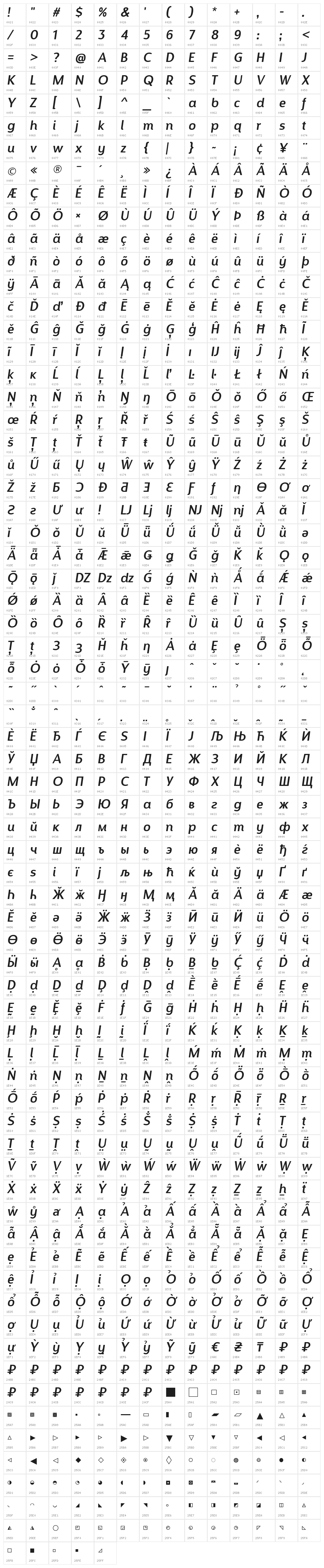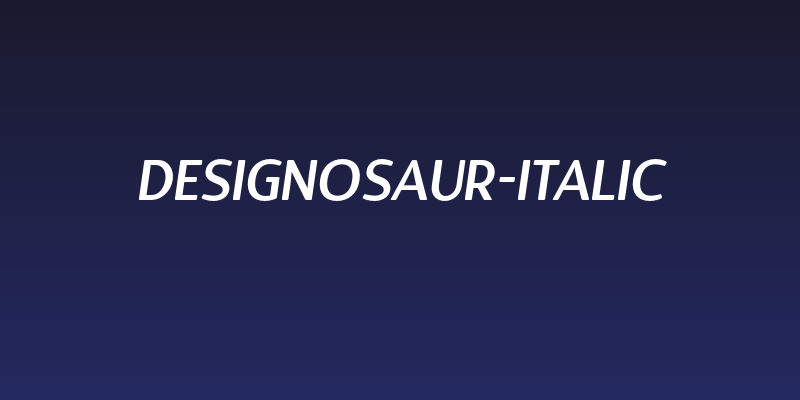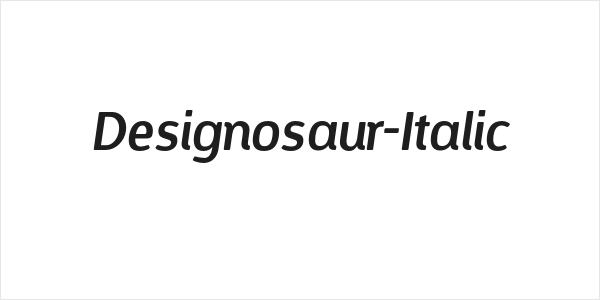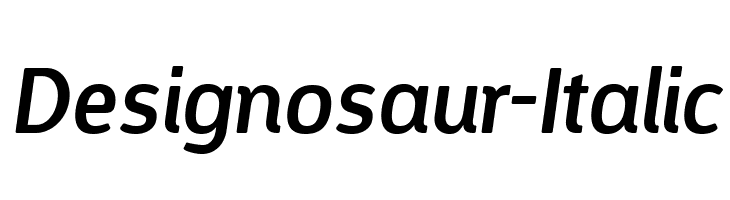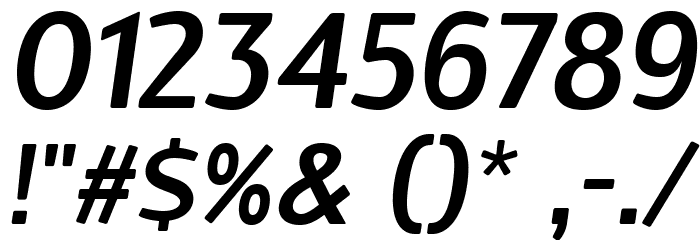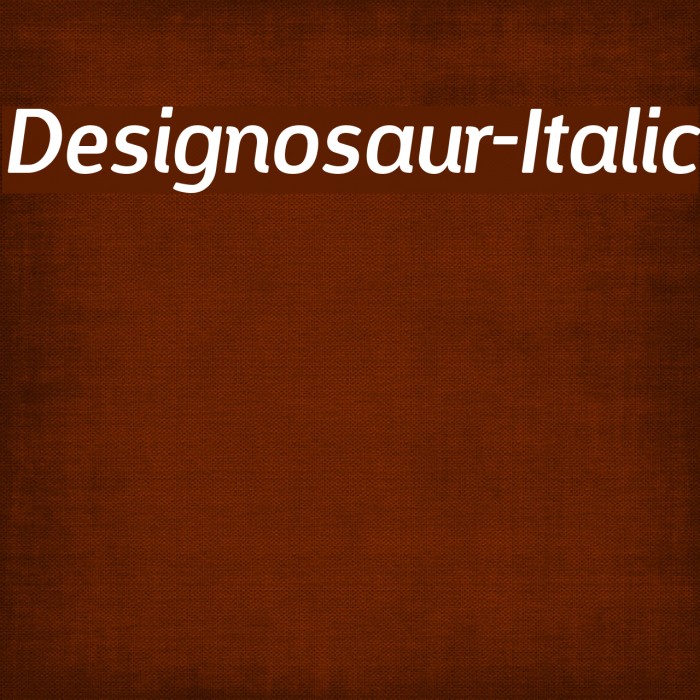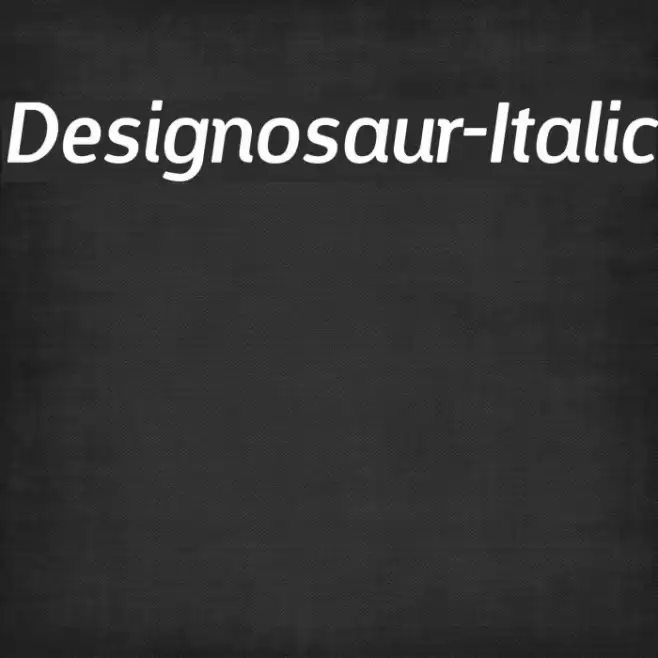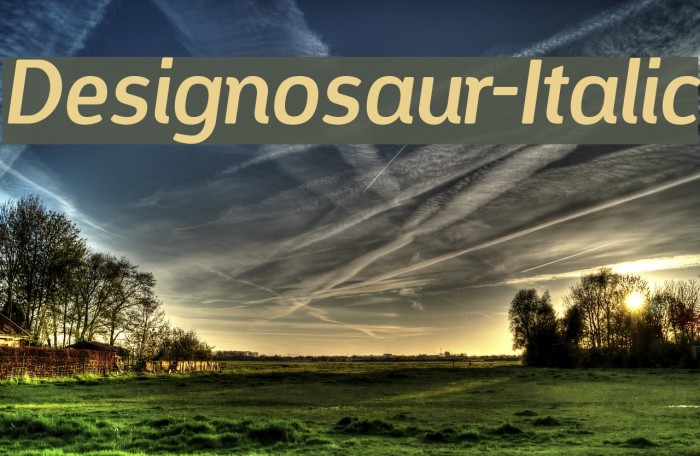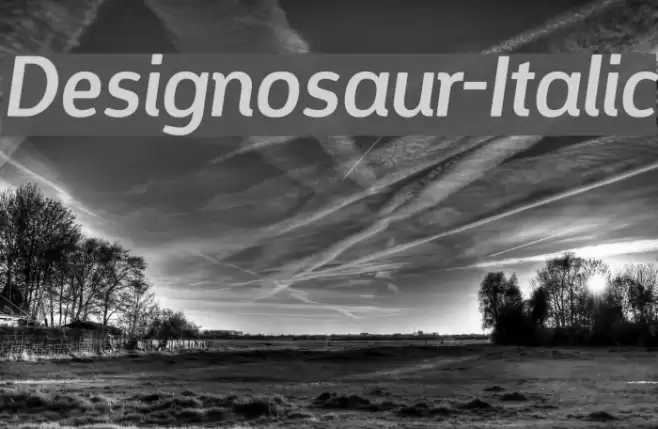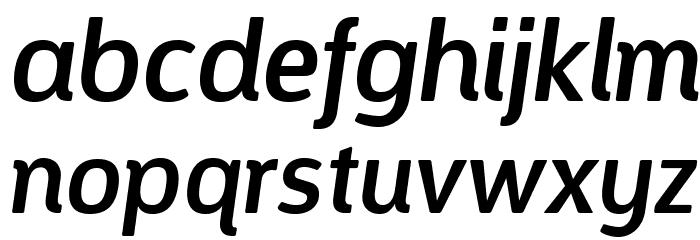
Designosaur-Italic Font
| 用途 | Headlines, Logos, Branding |
| おすすめプロジェクト | Ideal for branding, advertising, and editorial design projects that require a modern and dynamic aesthetic. |